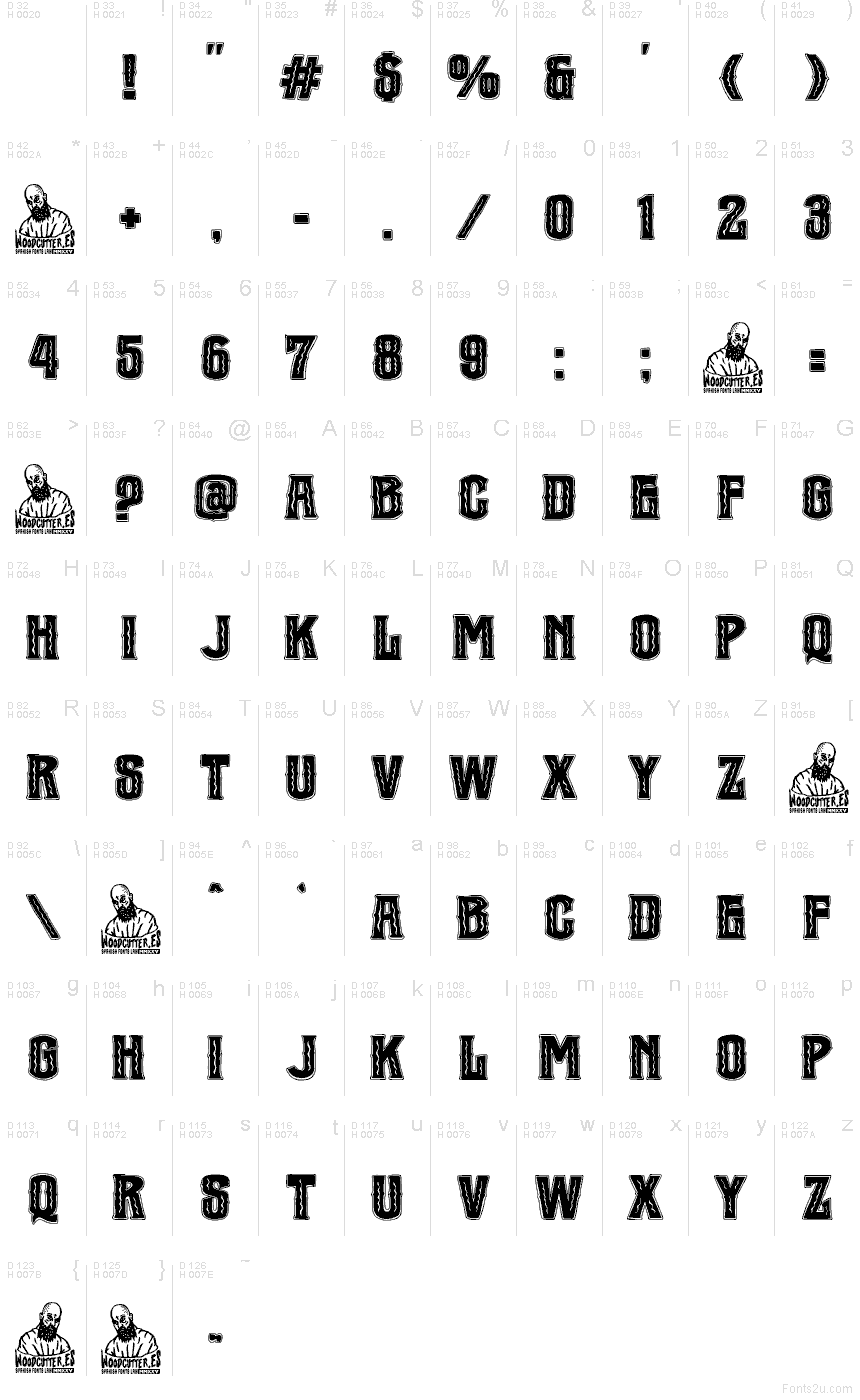
Bourbon Club Black
Bourbon Club Black di Woodcutter Manero è un font display in stile western gratuito, che cattura lo spirito delle vecchie insegne dei saloon e delle etichette del whiskey. Le maiuscole sono ampie e massicce, con luci interne scolpite e bordi irregolari e usurati che conferiscono alle lettere un aspetto vissuto, segnato e un po' ribelle.
Si adatta perfettamente a loghi di bar, etichette di bottiglie, titoli di poster, flyer per eventi e copertine che richiedono quel tocco "frontiera" senza risultare eccessivamente stravaganti. Come font gratuito per titoli, intestazioni di menù o grandi iniziali in stile monogramma, funziona alla grande perché le lettere possiedono già un carattere e una grana unici.